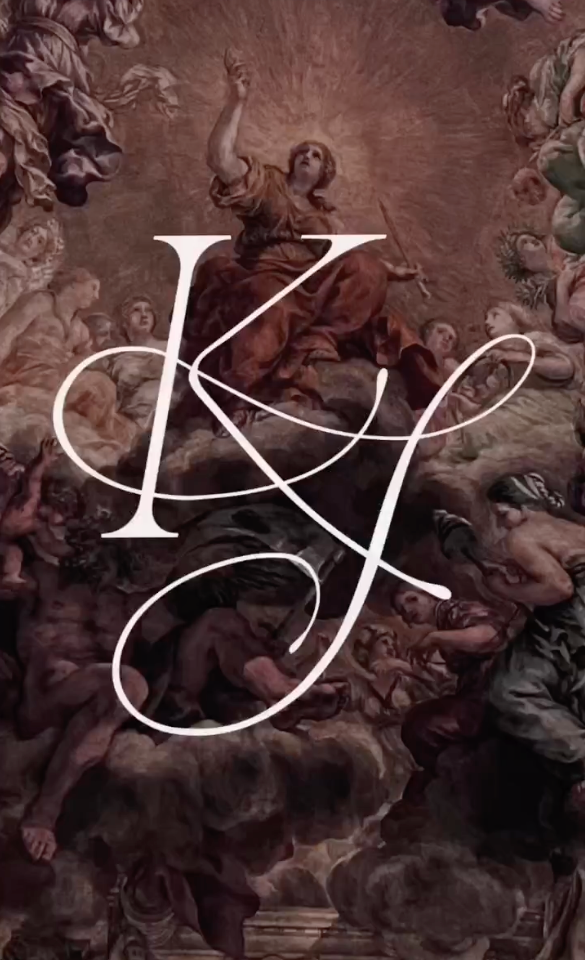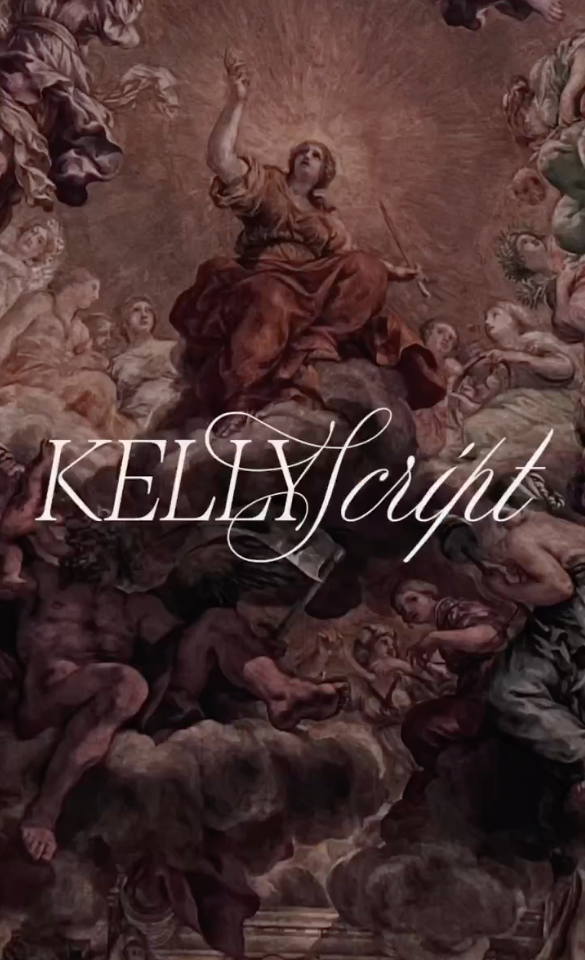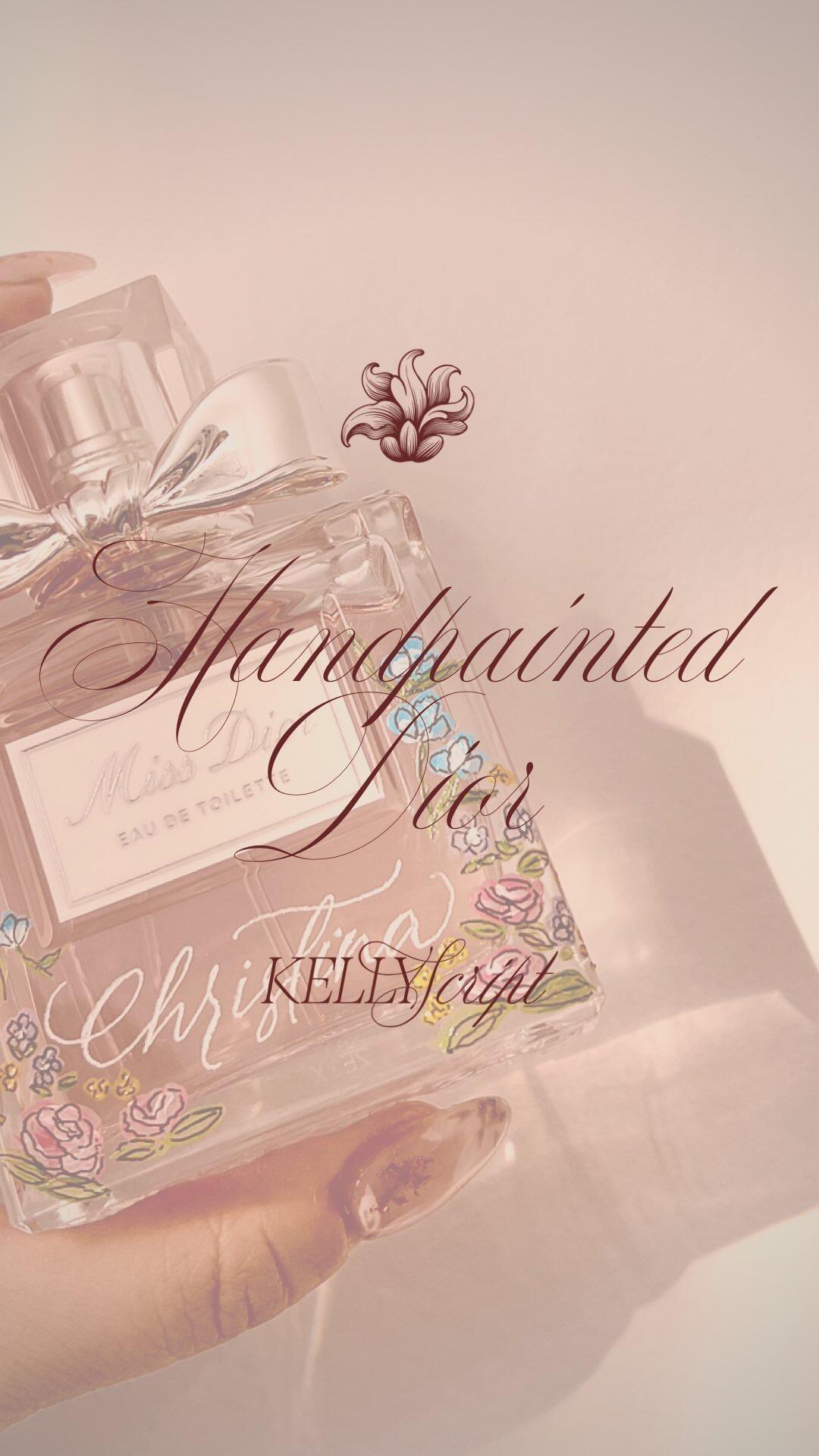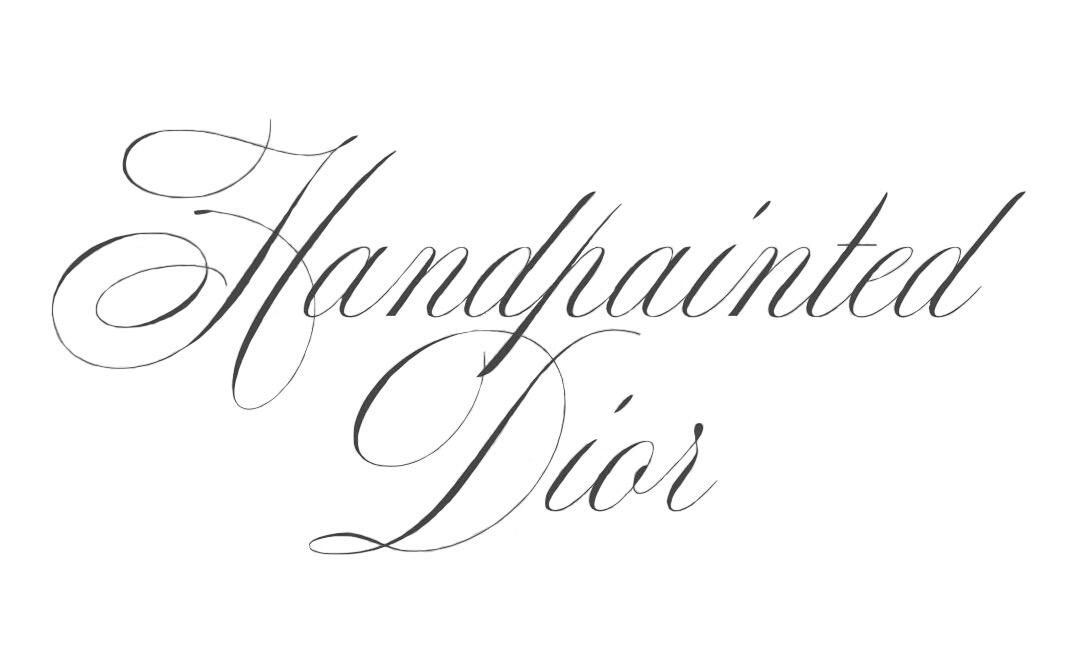
Suche zwei Schriften aus dem Branding für KELLY Script (Kalligrafie-Künstlerin)
Liebe Community. Ich bin auf der Suche nach zwei Schriften (exakt), die in einem Logo bzw. Schriftzug für ein Branding genutzt wurden – die Schriften dürfen natürlich kostenpflichtig sein 😉 Eine Script- und eine Serif-Schrift.
Ursprünglich auf Pinterest entdeckt, aber durch Recherche sehr schnell herausgefunden, wer das Branding gestaltet hat.
Ich habe auch beide schon direkt über Social Media angeschrieben und gefragt – die Designerin und die Kalligrafie-Künstlerin. Leider hat mir keiner der beiden geantwortet. Sämtliche Font Identifiyer Tools sind ebenfalls kläglich gescheitert (vor allem bei der Script Schrift sind die Ergebnisse noch total unbrauchbar). Ich vermute, so bald wir die KI das menschliche Auge und das historische Know-How in so feinen Bereichen wie Typografie noch nicht ersetzen können ;)
- Logo KS
- Logo KELLY Script ausgeschrieben
- Bild mit „Handpainted Dior“
- Bild mit „Handpainted Dior“ freigestellt